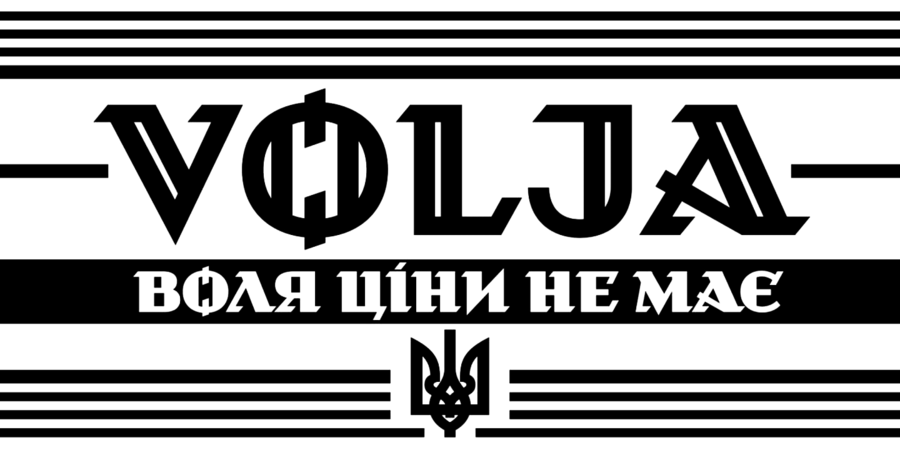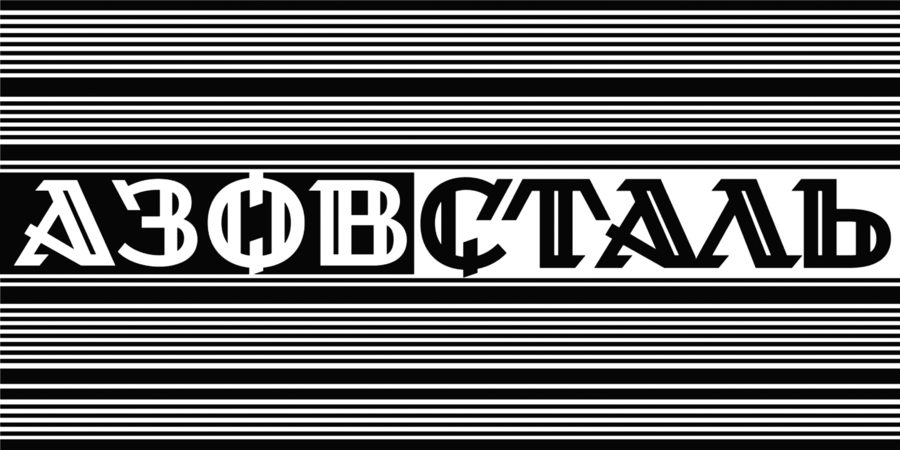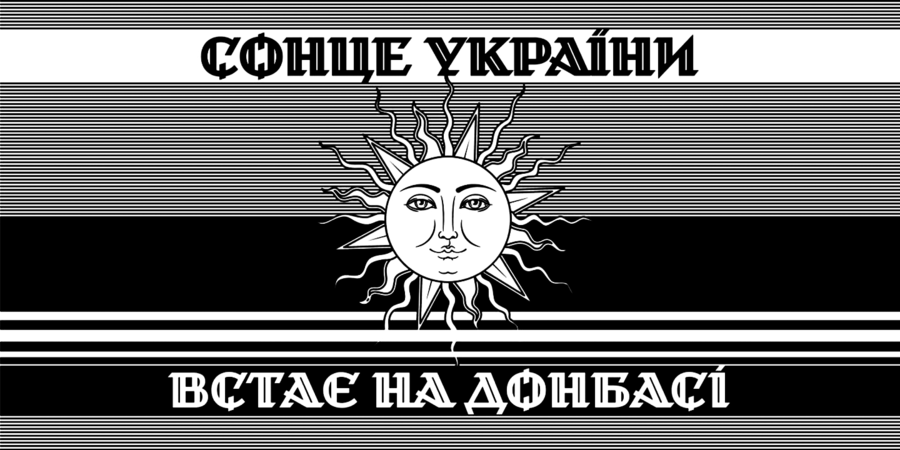
Опис гарнітури VoljaАкцидентний шрифт Воля у двох накресленнях зроблений з літерації українського графіка Ніла Хасевича (1905-1952) який оформлював плакати, журнали, газети для українського визвольного руху середини 20 століття. Найближчим аналогом для форми літер став титульний лист літературного журналу «За волю нації». У 2023 році Volja став офіційним церемонійним шрифтом Збройних Сил України. Шрифт розробила Марчела Можина у 2022 році.
Асоціації з сімейством шрифтів VoljaОсобистість і характер гарнітури:
сильний, твердий, оригінальний, характерний, гострий, різкий, чіткий, серйозний, жорсткий, залізний, сталевий, міський, стійкий, незвичайний, гордий, динамічний, артистичний, авторитетний, переконливий, важливий, архітектурний, впевнений, яскравий, помітний, амбітний, експериментальний, активний, виразний, якісний, дзвінкий, грубий, трикутний, кристальний, колючий, дивний, самобутній, сміливий, екстравагантний, мотивуючий, творчий, гучний, нав'язливий, небезпечний, екстремальний, ризикований, експресивний, зухвалий, пафосний, історичний, колоритний, ностальгічний, ремісничий, значний, суворий, старомодний, олдскульний, міцний, надійний, цікавий, урочистий, військовий, політичний, вольний, запальний, важкий, урбаністичний, потужний, агресивний, радикальний, епатажний, ламаний, революційний, вибуховий, кричущий, брутальний
архітектура, Трофей, нагорода, музей, скульптура, меч, гра, шоу, ніж, алкоголь, горілка, анімація, театр, реклама, каскадер, екстрим, байкер, металіст, концерт, електрогітара, рок-н-рол, геральдика, пам'ятник, меморіал, замок, банкнота, козак, гетьман, закуска, спеції, пиво, таверна, ремесло, коваль, тютюн, тату, татуювання, історія, реконструкція, сувенір, вишиванка, етнографія, монета, туризм, карти, прапор, Місто, одяг, взуття, інструмент, верстат, інсектицид, пестицид, супергерой, шолом, шутер, екшен, блокбастер, бойовик, м'ясо, війна, рок, страйк, Протест, реп, бомба, комп'ютерна гра, граніт Гарнітура асоціюється з віком: